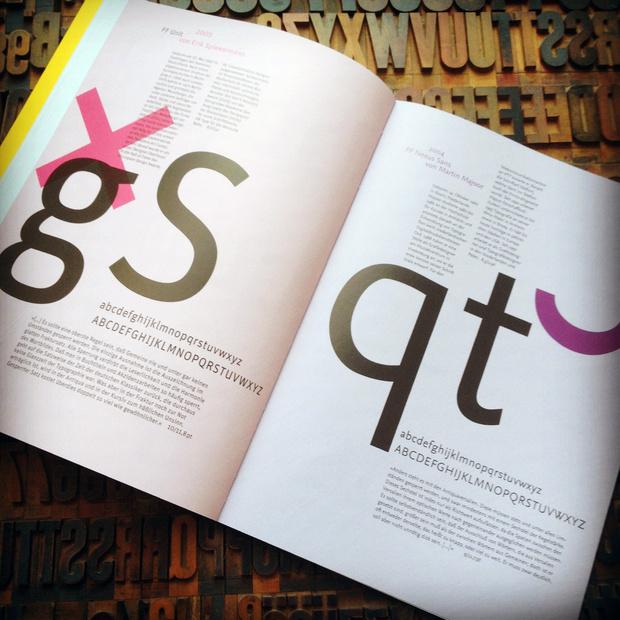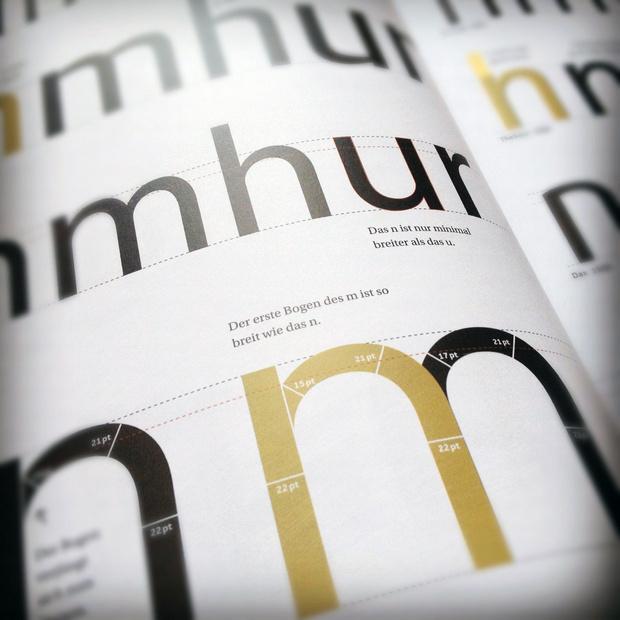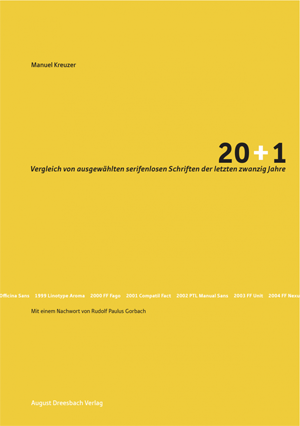
Im »August Dreesbach Verlag« ist das Buch 20+1. Vergleich von ausgewählten serifenlosen Schriften der letzten zwanzig Jahre von Manuel Kreuzer erschienen.
Es entstand als Studie im Rahmen des Jahreskurses Typografie der tgm München unter der Leitung von Rudolf Paulus Gorbach.
Der Autor Manuel Kreuzer untersucht in dieser Arbeit ausführlich 21 Schriften, die in den letzten 20 Jahren erschienen sind. Namentlich und in chronologischer Reihenfolge sind dies Quay Sans, DTL Argo, Myriad, Scala Sans, TheSans, DIN, Dax, Corpid, ITC Officina Sans, Linotype Aroma, FF Fago, Compatil Fact, PTL Manual Sans, FF Unit, FF Nexus Sans, Monitor, Phoenica, Candara, Museo Sans, Secca und Carter Sans.
Nach einem kurzen Einblick in die Entstehung der serifenlosen Schriften und deren Klassifikation geht es dann in den weiteren Kapiteln und die detaillierte Untersuchung der Schriften. Das Buch macht dabei da weiter, wo beispielsweise Anatomie der Buchstaben aufhört. Befasst sich letzteres noch sehr allgemein mit den Formprinzipien der lateinischen Buchstaben, geht es in 20+1 ans Eingemachte und die Unterschiede der untersuchten Schriften werden in akribischer Detailarbeit herausgearbeitet. Im ersten Kapitel werden die Größenverhältnisse der Klein- und Großbuchstaben untersucht. Kapitel zwei beschäftigt sich mit den Versalien und Kapitel drei mit den Minuskeln. Die Ergebnisse werden in ansprechender und übersichtlicher Weise auf großzügig gesetzten Doppelseiten dargelegt. Zudem gibt es zu jedem Schriftgestalter eine kurze Vorstellung des Werdegangs.
Eine der wichtigsten Einschätzungen bei einer Buchvorstellung ist natürlich immer die Frage, für welche Leser das Buch zu empfehlen ist. Bei diesem Werk fällt es mir allerdings schwer, darauf eine Antwort zu geben. Denn das Werk nennt sich ja nicht ohne Grund »Studie«. Es wurde weniger als Fachbuch mit einer bestimmten Zielgruppe im Sinn entwickelt, sondern fungiert als Dokumentation der Arbeit von Manuel Kreuter im Jahreskurs Typografie. Im Nachwort schreibt der Autor auch folgerichtig, dass er persönlich viel über die Anatomie der Buchstaben gelernt hat; dass sein Blick für diese Details nun geschärft ist und er in Kundengesprächen nun sicherer argumentieren kann. Dies mag man ihm gern glauben. Ob andere Schriftanwender jedoch durch den Kauf dieses Buches ebenfalls so tief in die feinen Details des Buchstabendesigns eintauchen wollen, bleibt abzuwarten. Empfehlenswert ist das Buch dagegen sicherlich für angehende Schriftgestalter.
Aus Leser-Sicht hätte ich mir zudem gewünscht, dass man die gefundenen Unterschiede der Schriften nicht nur einzeln aufgezeigt, sondern auch miteinander in Beziehung setzt. Die bewusste Verteilung der Schriftauswahl auf die letzten 20 Jahre legt ja förmlich die Frage nahe, wie sich die Schriftgestaltung in diesem Zeitabschnitt gewandelt hat und welche Einflüsse dafür verantwortlich sein könnten. Entsprechende inhaltliche Auseinandersetzungen liefert das Buch jedoch nicht. Der Leser muss seine eigenen Schlüsse aus den einzelnen Untersuchungen ziehen.